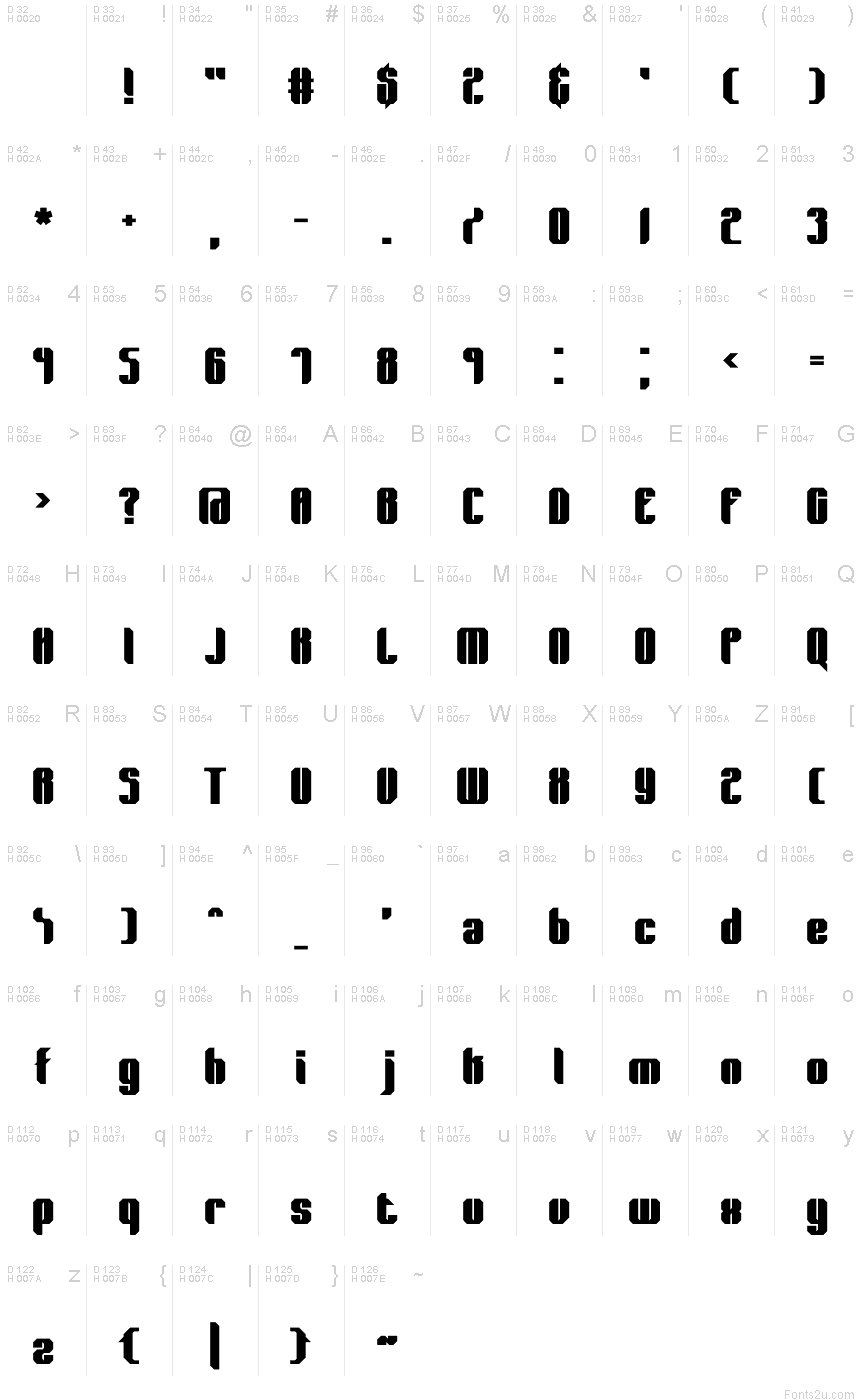
Wager BRK od ÆNIGMA Fonts to darmowy font typu display, który łączy styl blackletter z techno, charakteryzujący się mocnym, plakatowym wyrazem. Litery czerpią z gotyckiej tekstury, ale ścięte narożniki, blokowa konstrukcja i zwarty rytm sprawiają, że dalekie im do nastroju dawnych rękopisów, a bliżej do czegoś syntetycznego i miejskiego.
Świetnie sprawdzi się na muzycznych ulotkach, w logotypach gier, grafikach streetwearowych, horrorowych tytułach czy wyrazistych nagłówkach, gdzie potrzebna jest szybka budowa atmosfery. Dzięki gęstym, zazębiającym się kształtom, które nie stają się przesadnie zdobne, font ten dobrze działa również w krótkim brandingu, monogramach i inicjałach, które wymagają średniowiecznego echa w nowoczesnym, mechanicznym wydaniu.
Wager BRK